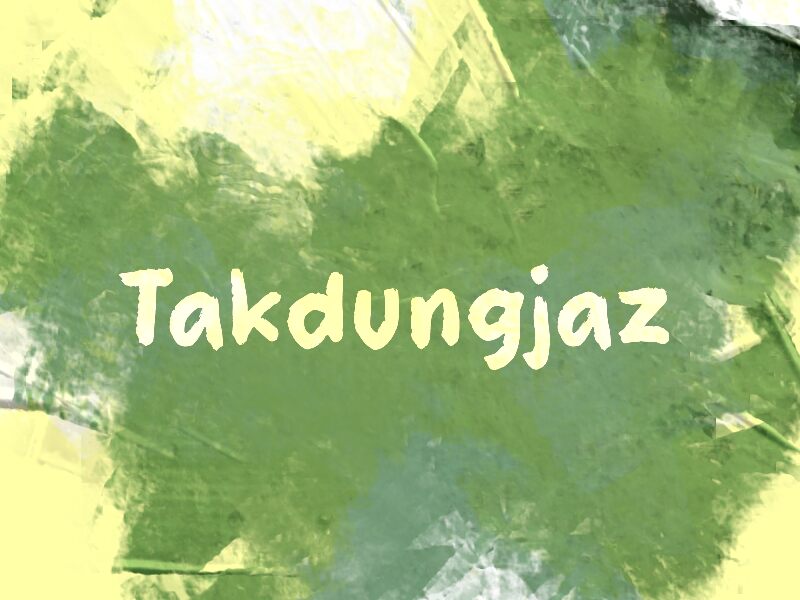
Takdungjaz, créée par Wep, est une police pinceau gratuite au style brut et peint à la main. Les lettres semblent avoir été appliquées au pinceau chargé de peinture, avec des traits épais, des jointures arrondies et des bords irréguliers qui conservent un rythme libre et humain, loin de tout aspect trop lisse.
Elle s'intègre naturellement dans les titres d'affiches, les pochettes d'albums, les graphismes streetwear, les couvertures de fanzines et les packagings décontractés où une police gratuite doit avoir un aspect immédiat et artisanal. Grâce à ses traits larges et légèrement irréguliers, Takdungjaz fonctionne mieux dans les mots courts, les titres et les logos percutants où cette texture peinte et spontanée peut exprimer tout son potentiel.
Takdungjaz
Présentation et spécimen de la police Takdungjaz